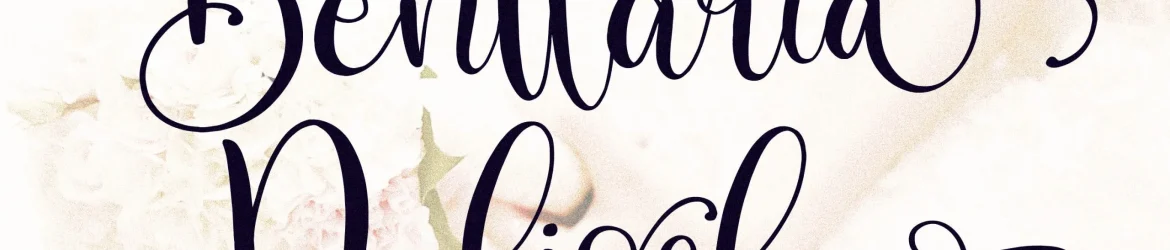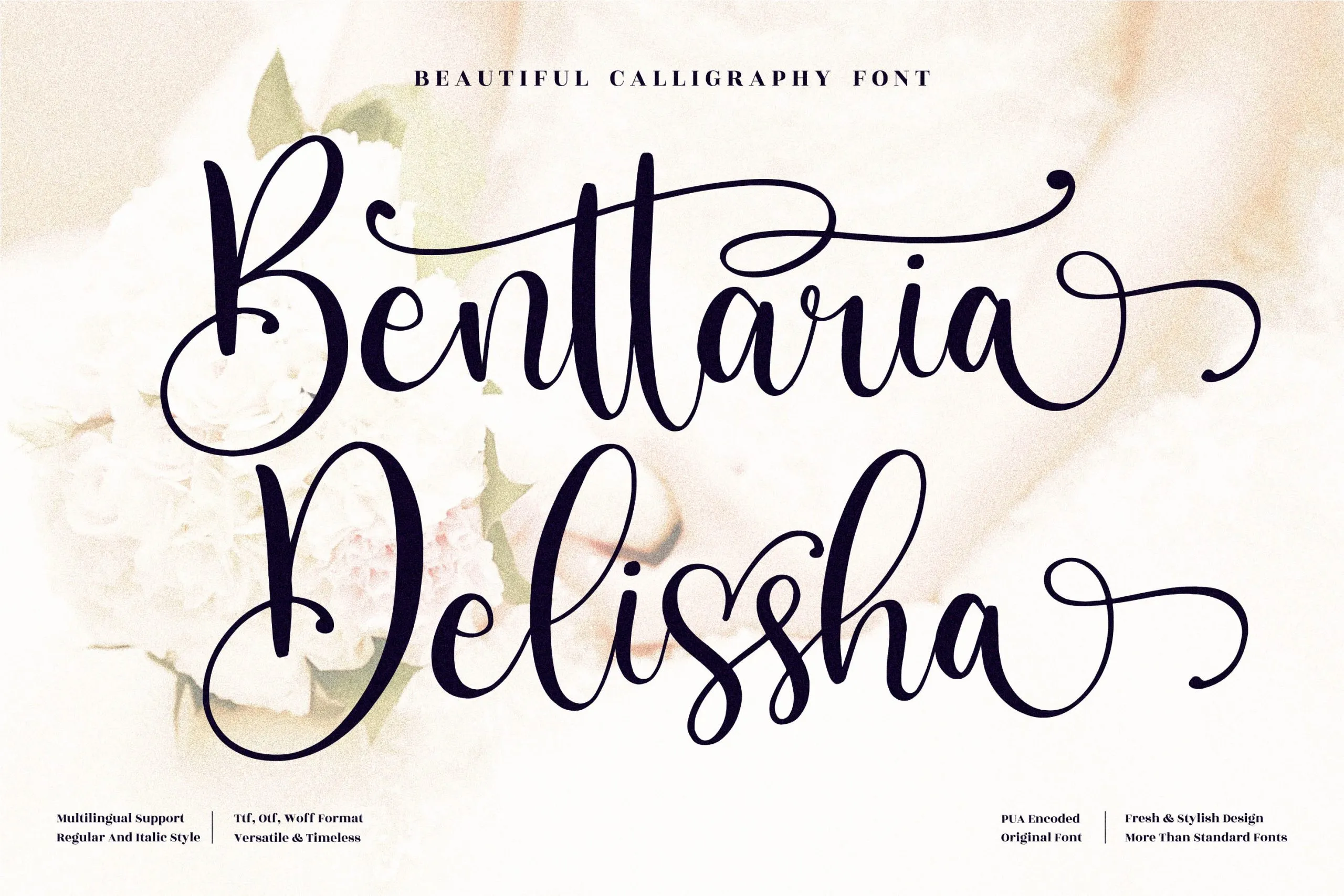
Benttaria Delissha Font
Esta é uma fonte de calligrafia romântica projetada para atender a diversos projetos que desejam incorporar um toque de elegância e delicadeza na sua criação. Ideal tanto para identidades visuais como para design do produto, desde marcas de empresas até embalagens de produtos, Benttaria Delissha é perfeita para qualquer projeto onde você deseja adicionar uma trama única e suave. Seja em mugs decorativos, cartões de agradecimento, capas de livros ou mesmo até mesmo em impressão em tela para camisas personalizadas, essa fonte vai agregar um toque diferenciado ao seu trabalho. Com Benttaria Delissha, você pode trazer uma sensação autêntica e criativa a projetos variados que requerem um acabamento cuidadoso e estiloso. Seja para criação de logomarcas, designs de mesa ou até mesmo para adicionar um toque especial em seus textos digitais, esta fonte será sua melhor aliada em criar belas obras de arte digitais.